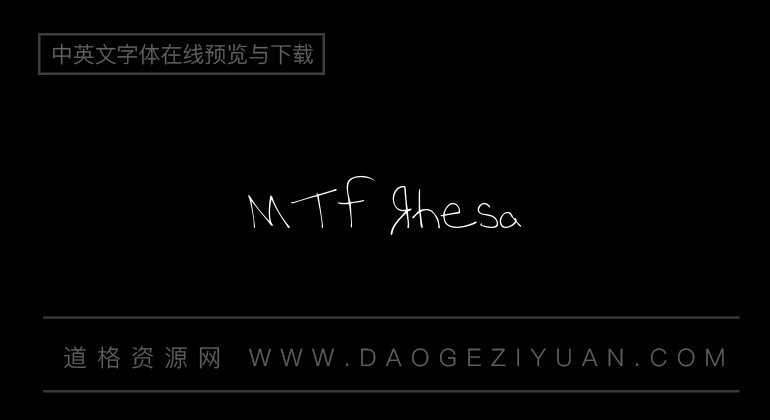
MTF Rhesa
MTF Rhesa 是一种非常流行的手写风格字体,它的设计灵感来自于意大利手写艺术家 Rhesa Montague。这种字体具有非常自然、手写的感觉,字形线条流畅、柔和,给人一种亲切、温暖的感觉。 MTF Rhesa 字体适用于各种设计场合,尤其适合用于浪漫、温馨、亲情等主题的设计,其手写风格可以为设计作品增添一份独特的个性和魅力。同时,该字体也非常适合用于卡片、书籍、海报和网站设计等场合,能够有效地传达出温暖和亲切的情感。 MTF Rhesa 字体可以免费下载和使用,并且有多种字重和风格可供选择,包括常规体、粗体、斜体等,可以根据设计需求灵活选用。
MTF Rhesa是一款非常不错的手写艺术字体,具有很好的视觉感,适合于文化类的宣传设计、商业类品牌的广告和产品包装设计以及个性化文字排版等较多场景。